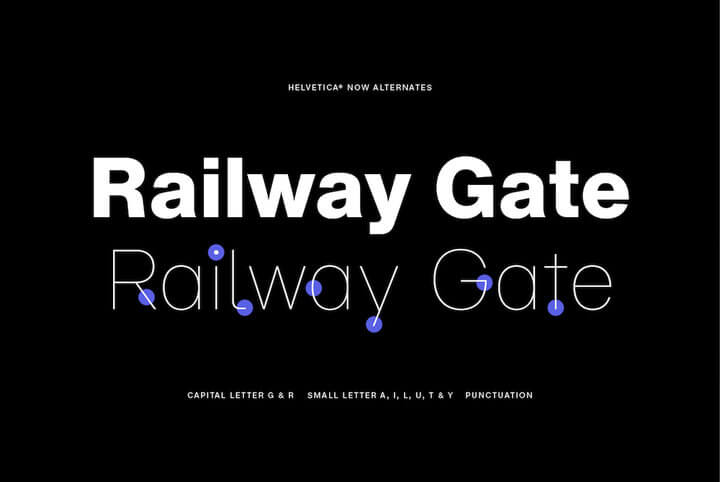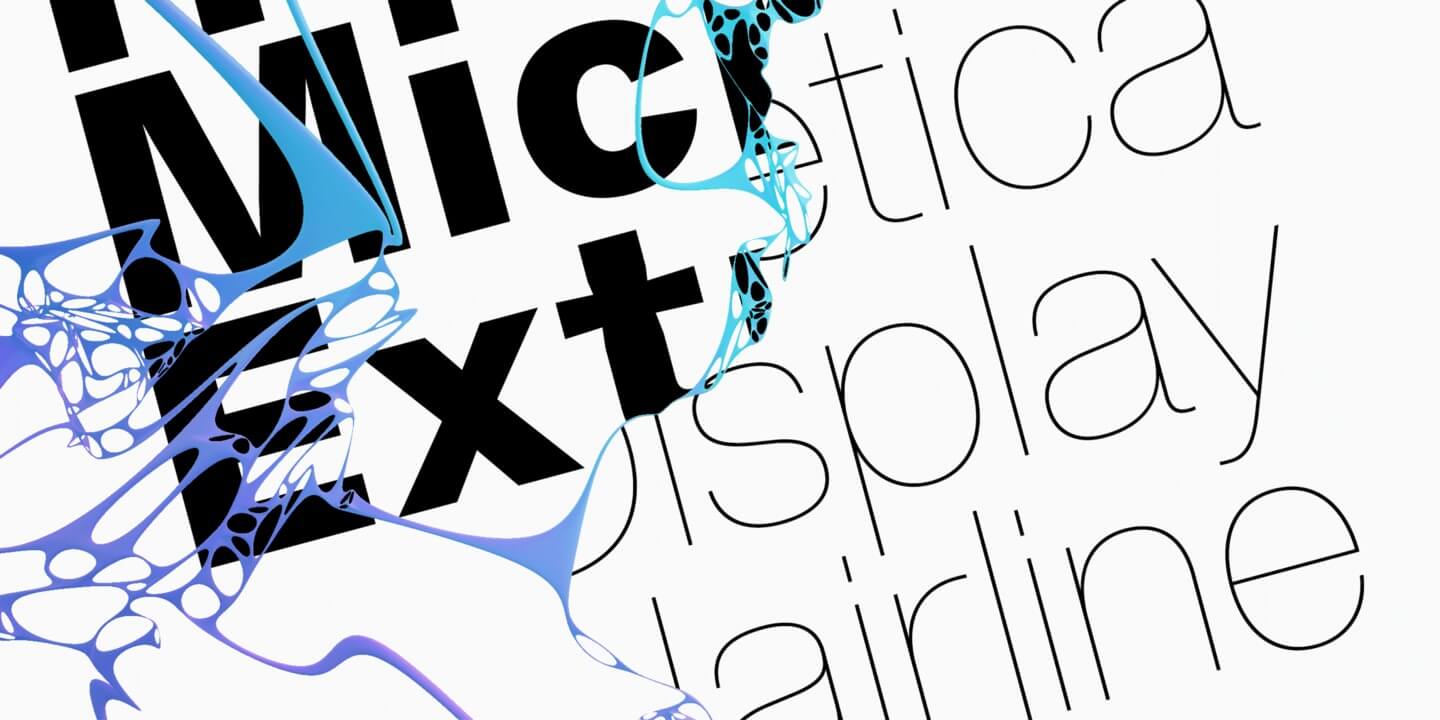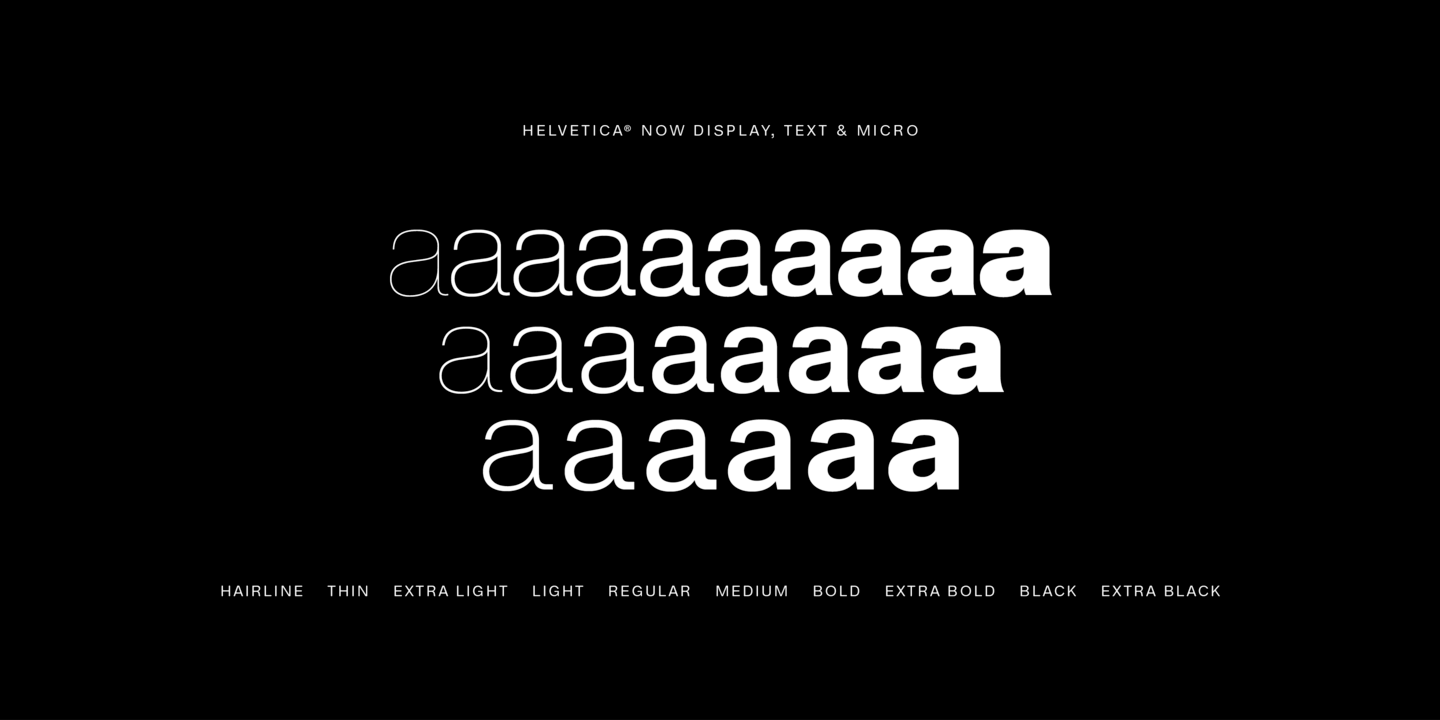
拉丁最经典的字体 Helvetica 进化版Helvetica Now
拉丁最经典的字体 Helvetica 进化版
Helvetica Now Display x20
Helvetica Now Micro x12
Helvetica Now Text x16
Helvetica® Now by Monotype